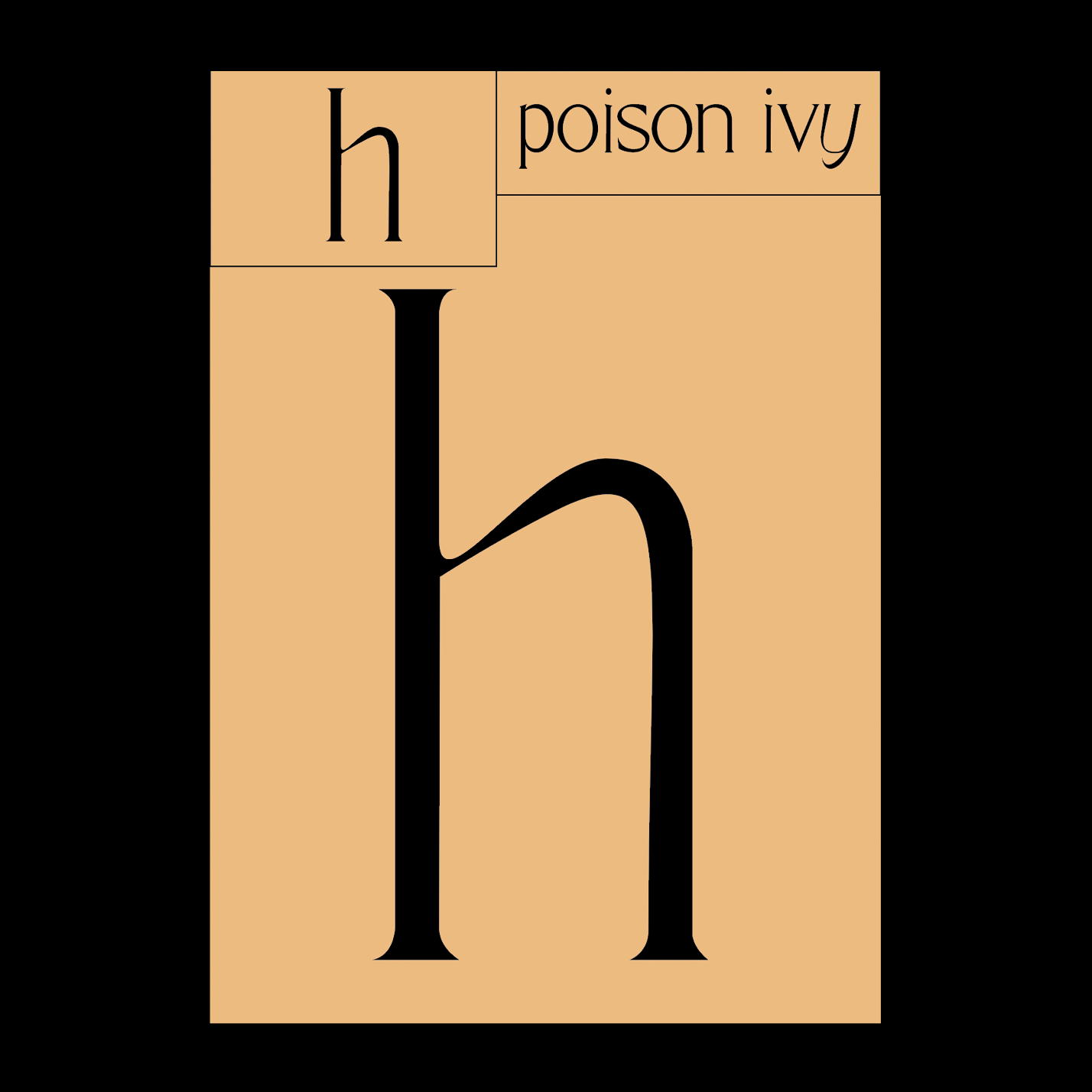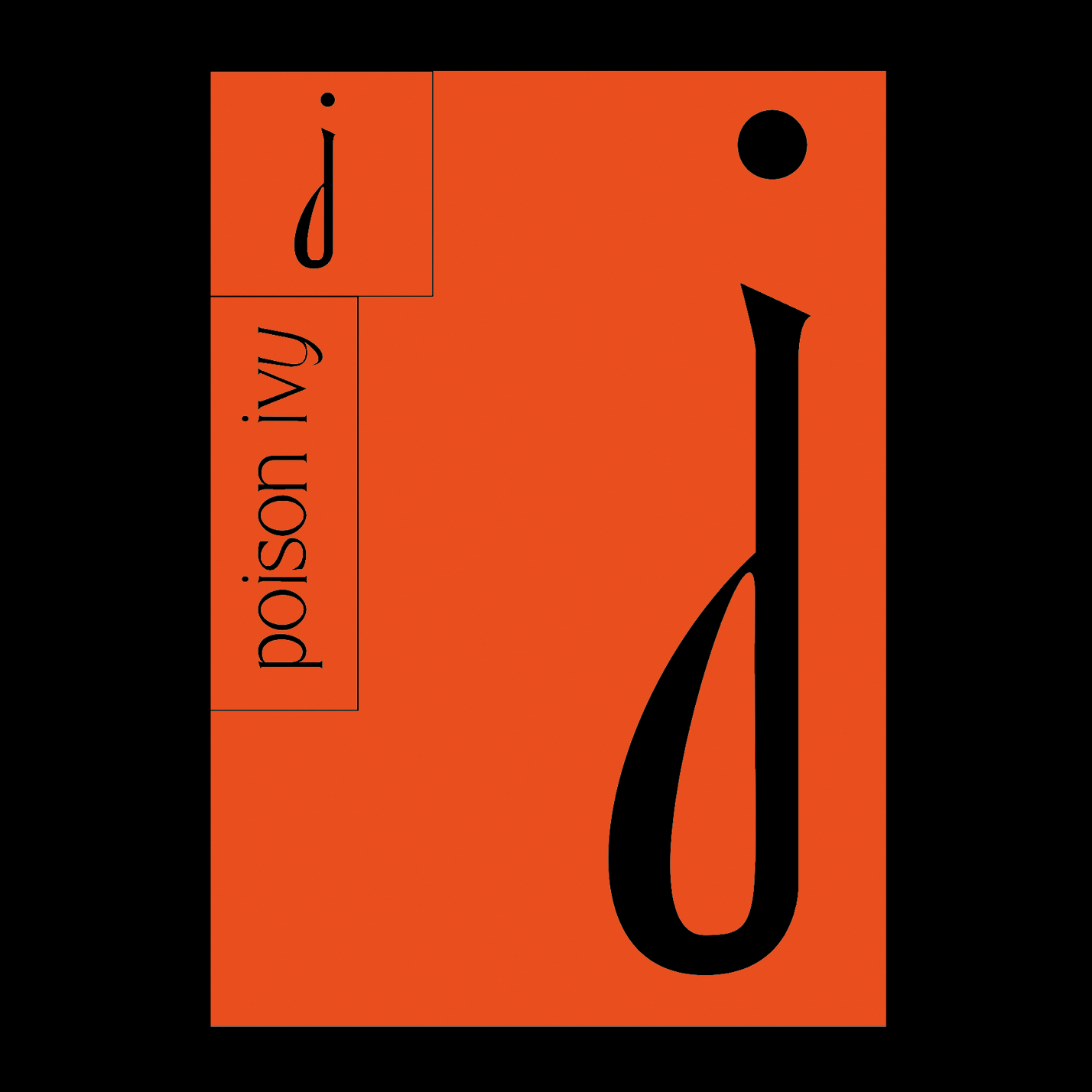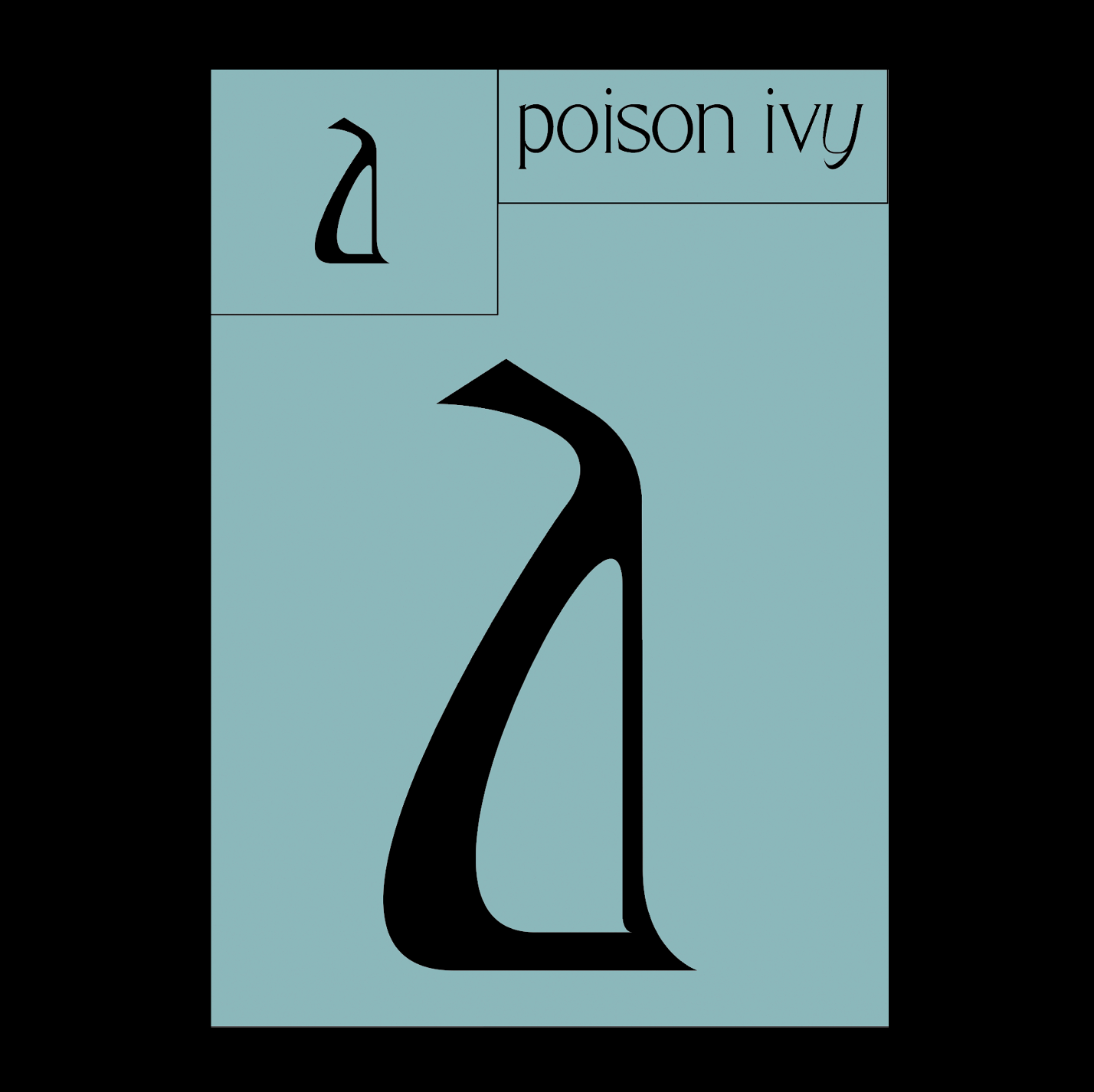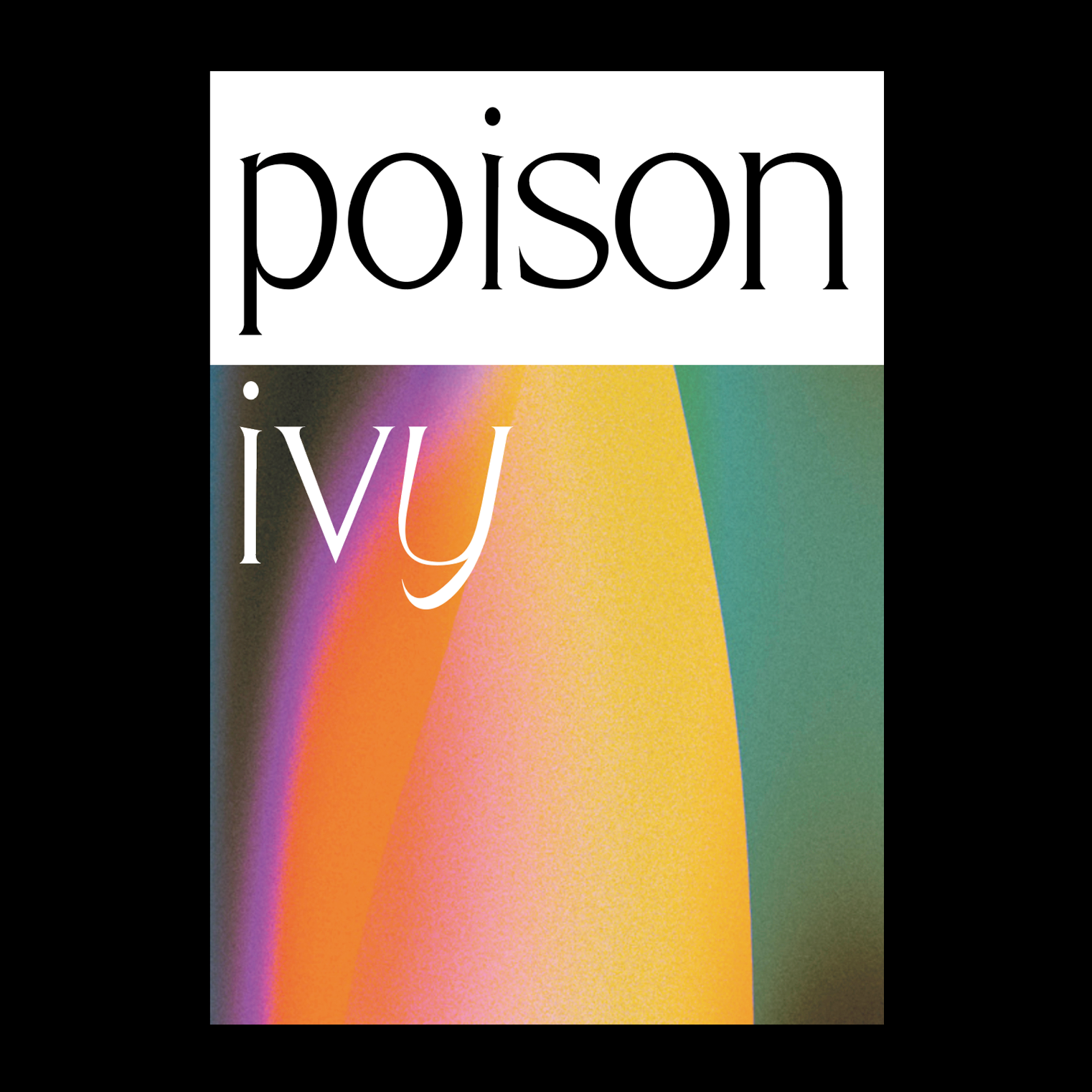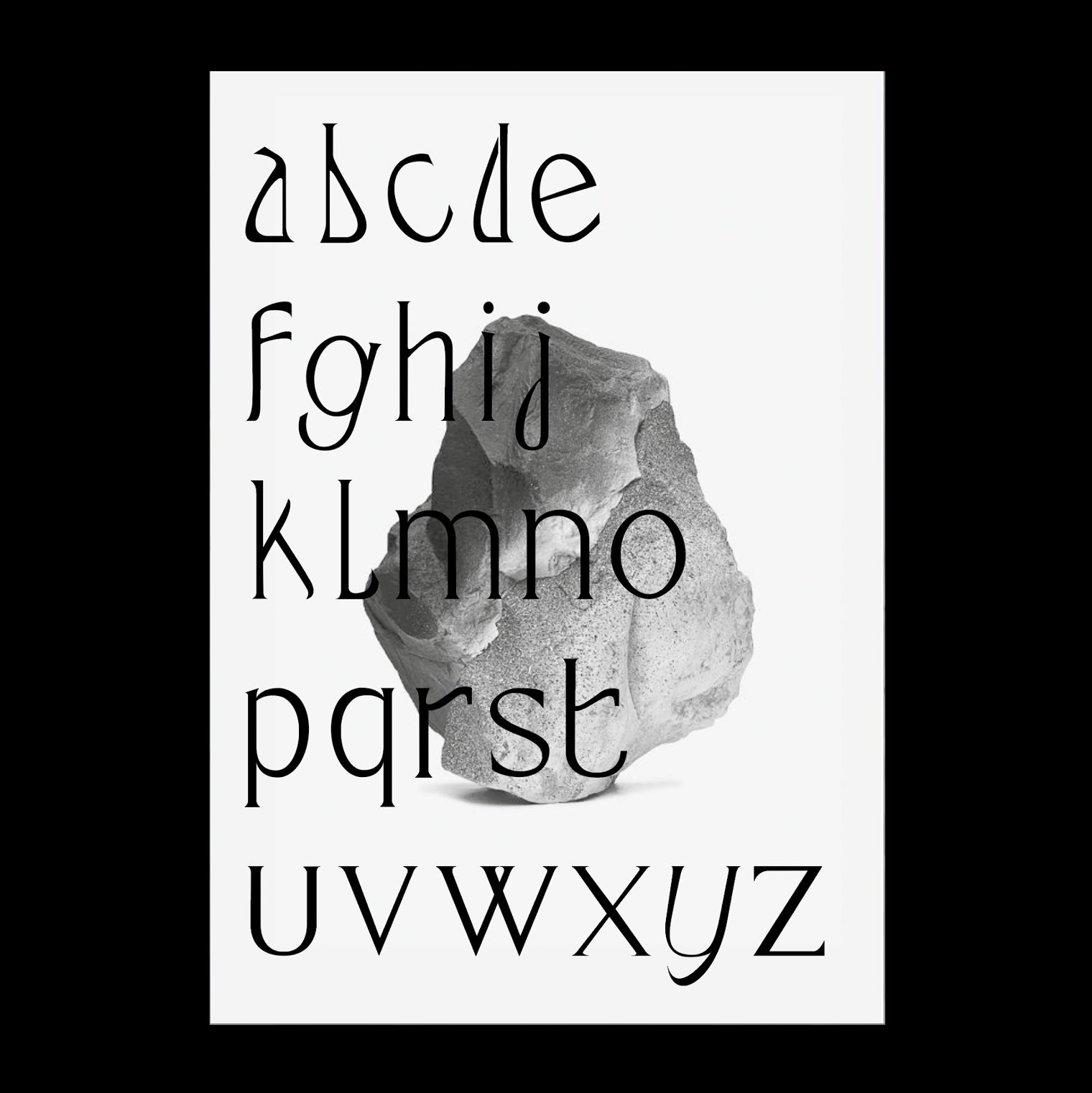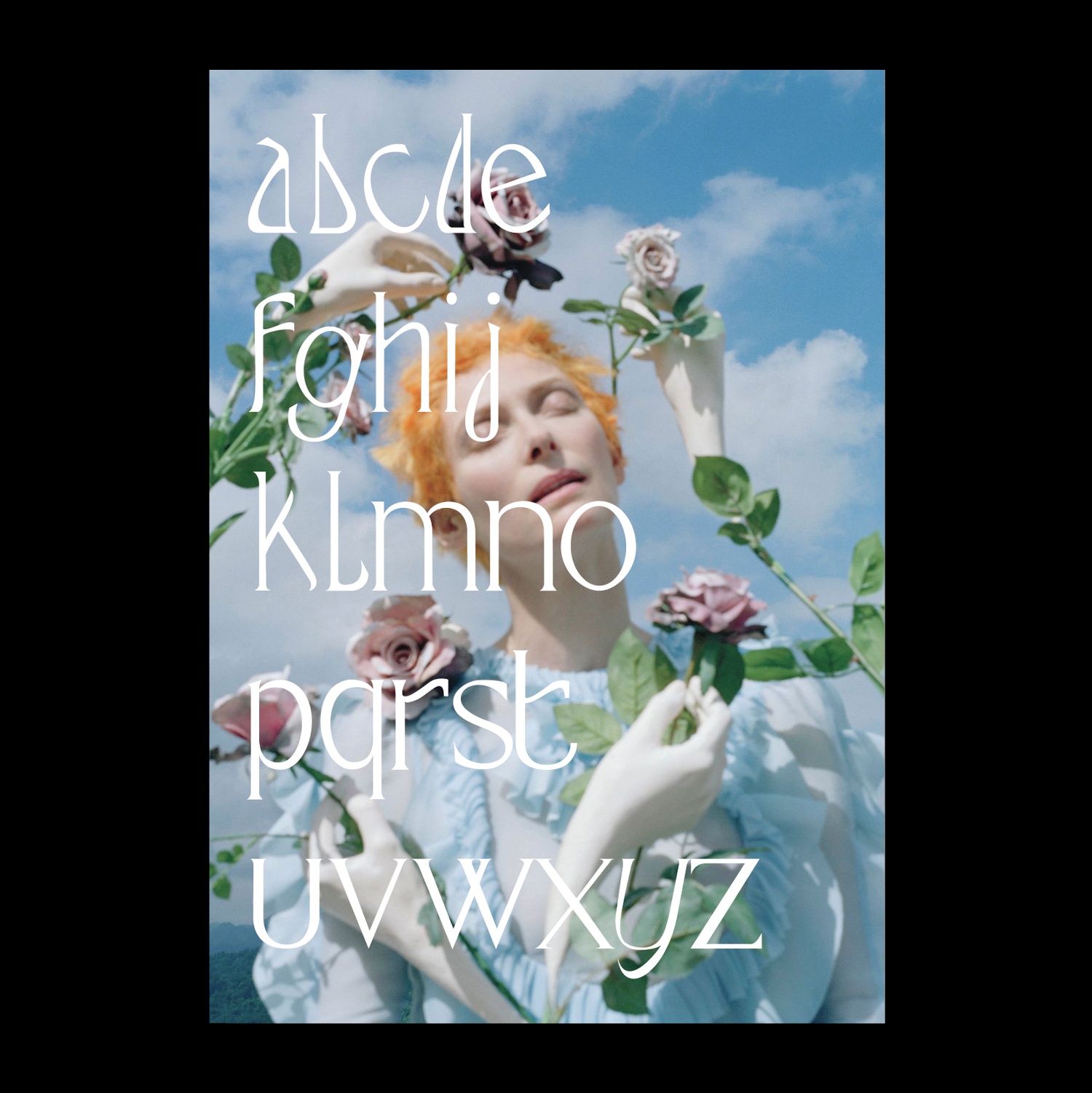
Poison Ivy est un prototype typographique conçu lors de ma première exploration du logiciel Glyphs. L’objectif était de traduire un univers végétal à la fois délicat et piquant, comme une rose et ses épines — d’où son nom. Les empattements, dessinés comme des pointes, évoquent cette dualité, tandis que la construction volontairement irrégulière fait écho à l’imprévisibilité de la nature.
Poison Ivy is a typographic prototype designed during my first exploration of Glyphs software. The goal was to convey a plant-like world that was both delicate and prickly, like a rose and its thorns—hence its name. The serifs, designed like spikes, evoke this duality, while the deliberately irregular construction echoes the unpredictability of nature.